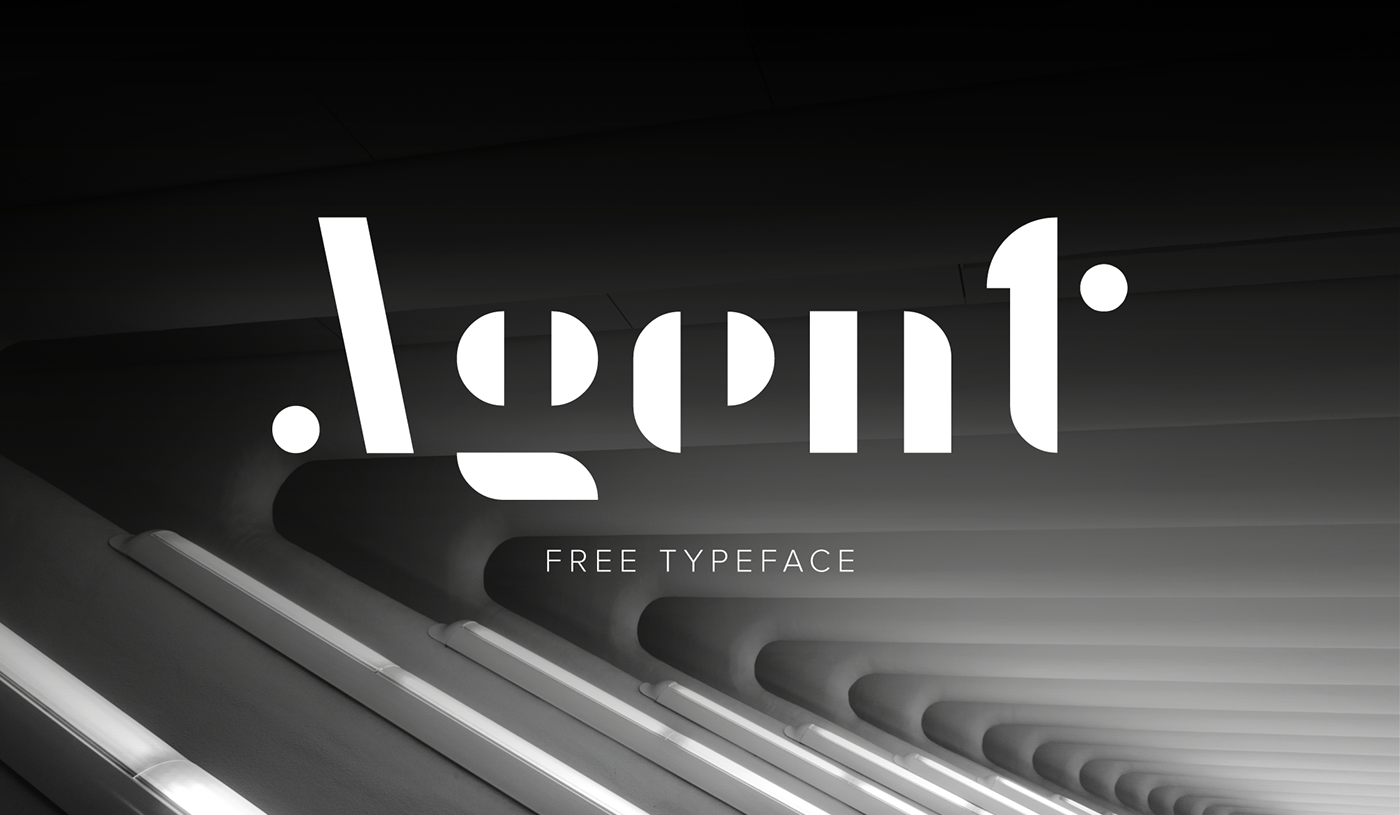
Agent Typeface – Download Grátis
Bem-vindo! Introduzimos a Agent Typeface! Desenvolvida e compartilhada por Mark O’Neill, essa fonte está apresentada num estilo tipo fontes abstratas estressadas com uma colina de cubismo. A Agent Typeface é perfeita para diversas aplicações, desde grunge até retro, oferecendo um toque único e interessante à sua próxima criação visual. Seja você designer de jogos digitais ou criador de conteúdo artístico, essa fonte será uma ótima escolha. Sempre procurando por novas opções para complementar seus projetos? A Agent Typeface pode ser a solução que está esperando!